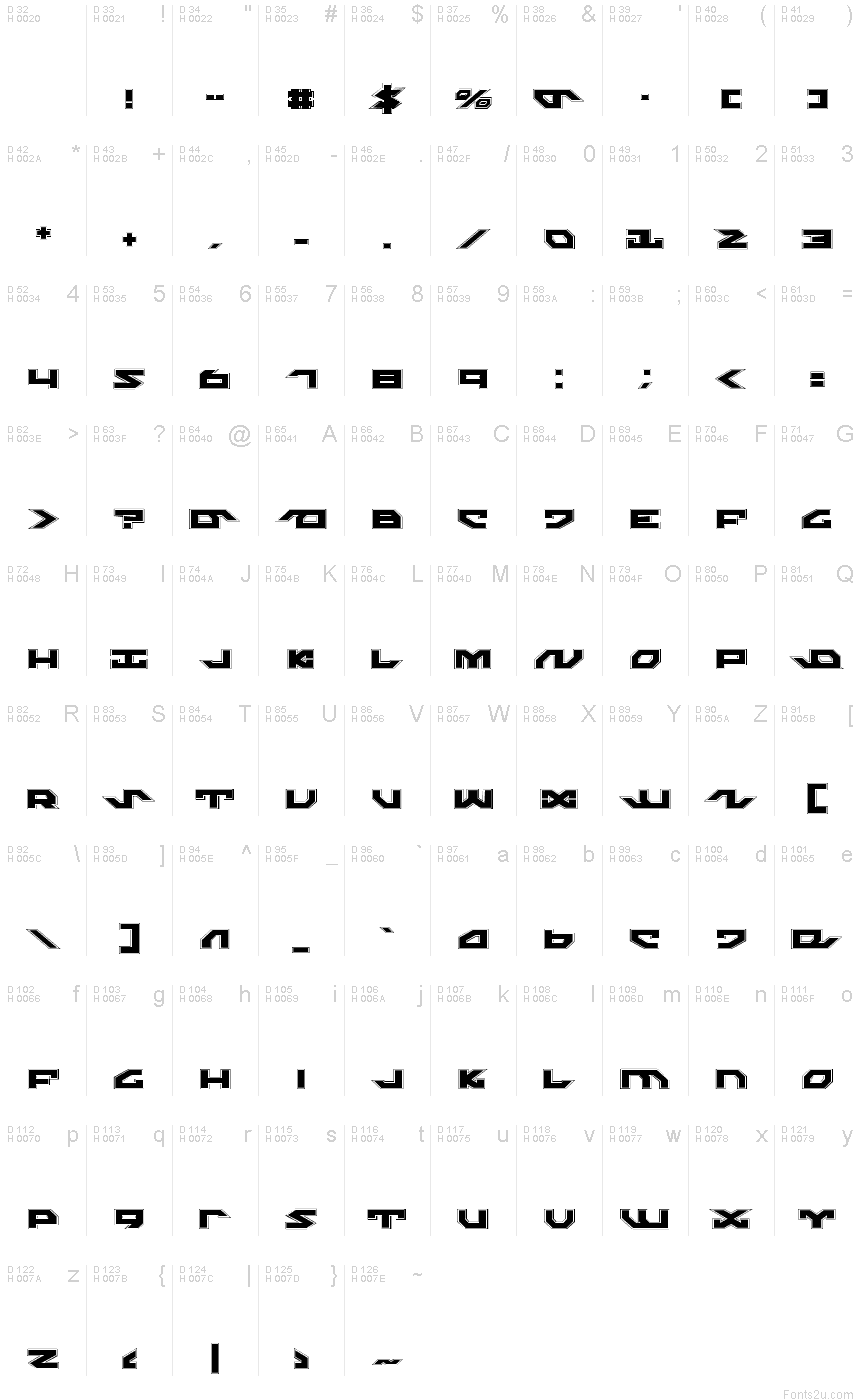
Nightrunner Pro di Iconian Fonts è un carattere techno futurista gratuito dal tratto deciso, ispirato ai circuiti stampati. Le lettere sembrano scolpite in moduli, con angoli squadrati, diagonali troncate e contorni in rilievo che donano al carattere un effetto neon a strati, senza però perdere il suo aspetto sci-fi austero.
Si adatta perfettamente a loghi di videogiochi, poster synthwave, flyer per club, titoli e branding tecnologico dove le parole brevi richiedono un ritmo meccanico. Essendo un carattere gratuito, è ideale anche per titoli di copertina, grafiche per streamer e monogrammi, soprattutto quando vuoi che le maiuscole sembrino percorsi interconnessi piuttosto che semplici lettere a blocchi.
Nightrunner Pro